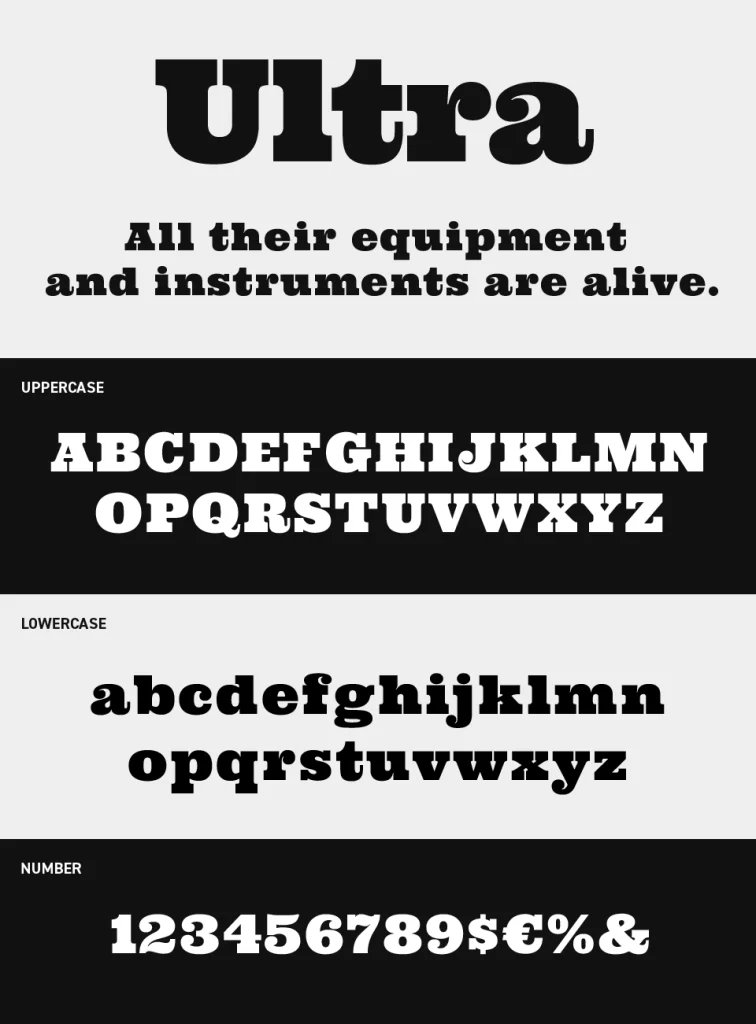
Ultra Font
Ultraフォン塔は、超極太のスラブセリフを採用した、クラシカルで重厚感あふれるディスプレイフォントです。
19世紀の木活字を思わせるどっしりとしたシルエットが特徴で、レトロな雰囲気と力強さを兼ね備えているコミカルなデザインです。見出しに配置するだけで、紙面全体に安定感と迫力を生み出してくれます。
横画・縦画ともに非常に太く設計されているため、小さな文字よりも大きなサイズで使用すると魅力が際立ちます。ヴィンテージポスターやアメリカンダイナー、西部劇、クラフトビールのラベルなど、懐かしさや重量感を演出したいデザインにぴったりです。